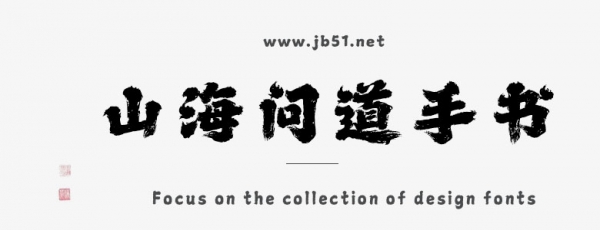
山海問(wèn)道手書(shū)W是由山海字庫(kù)出品的字體,這款字體筆觸略粗,具有很好的視覺(jué)感,適合應(yīng)用于藝術(shù)設(shè)計(jì)、平面宣傳設(shè)計(jì)、網(wǎng)頁(yè)設(shè)計(jì),書(shū)法字帖等領(lǐng)域,需要的朋友可以前來(lái)本站下載。